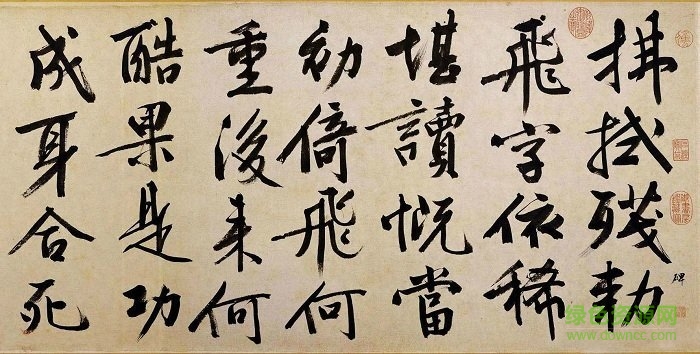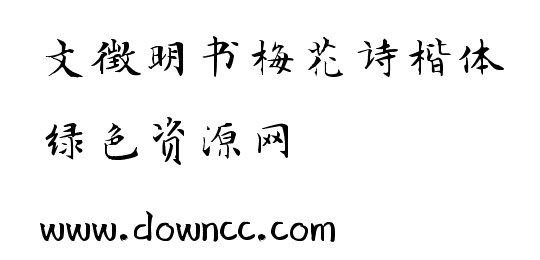
文徵明書梅花詩楷體
文徵明梅花詩楷體是明代文征明83歲書法作品《梅花詩》的衍生字體,講原版的行書換成了更加溫婉、實用性廣泛的楷書字體,別有一番風味,喜歡的朋友就來綠色資源網(wǎng)體驗吧!
文徵明書梅花詩楷體字體特色
文徵明唐朝體筆畫粗壯,尾部的甩尾有力且有豐富的筆觸細節(jié),大字效果突出且引人注目;并且最大程度還原作者書寫字形,細節(jié)表現(xiàn)完整,非常的文雅脫俗,整體效果十分酷炫好看,盡顯書法大師的魅力。
文徵明書梅花詩
文徵明梅花詩楷體字體綜合了柳公權、顏真卿、歐陽詢等唐代最高水平書法家的運筆特點,兼顧參考了八世紀雕版木刻印刷的特點。
拉丁字母部分,創(chuàng)新的采用了同時期拉丁字母使用地區(qū)的書寫風格。避免了以中文字體筆畫生搬硬套的中文字體配套字母的常見做法,使混排效果更加和諧。